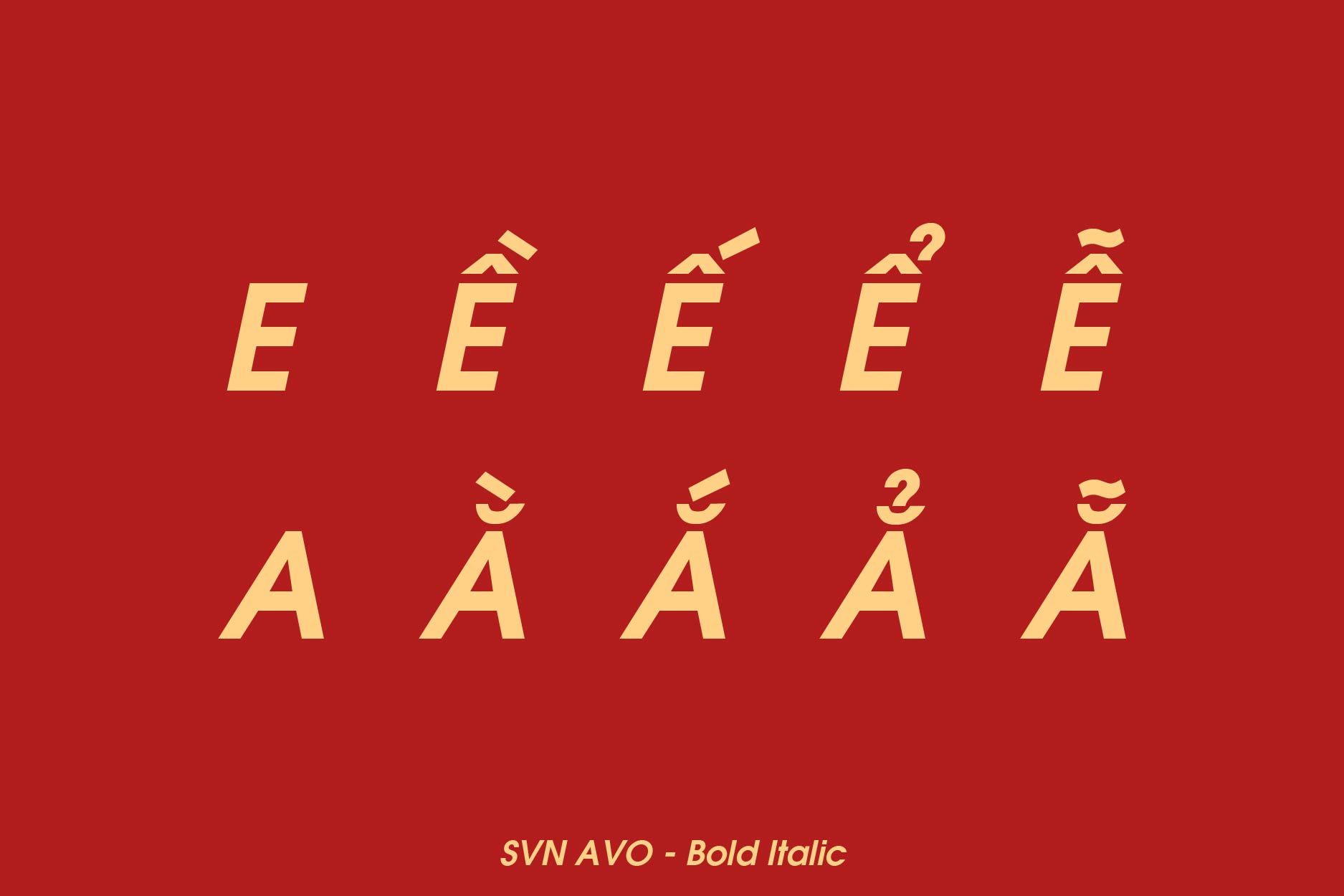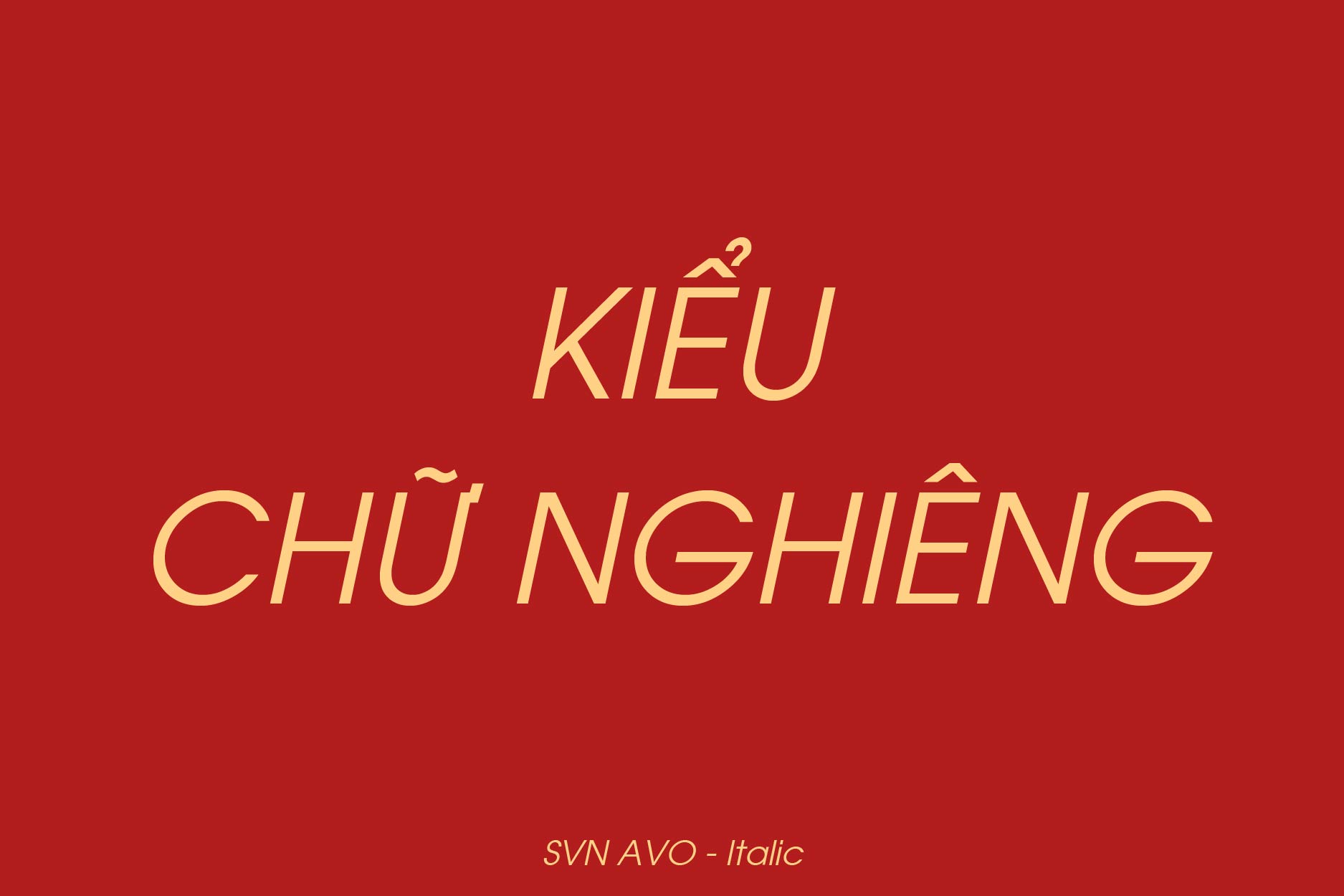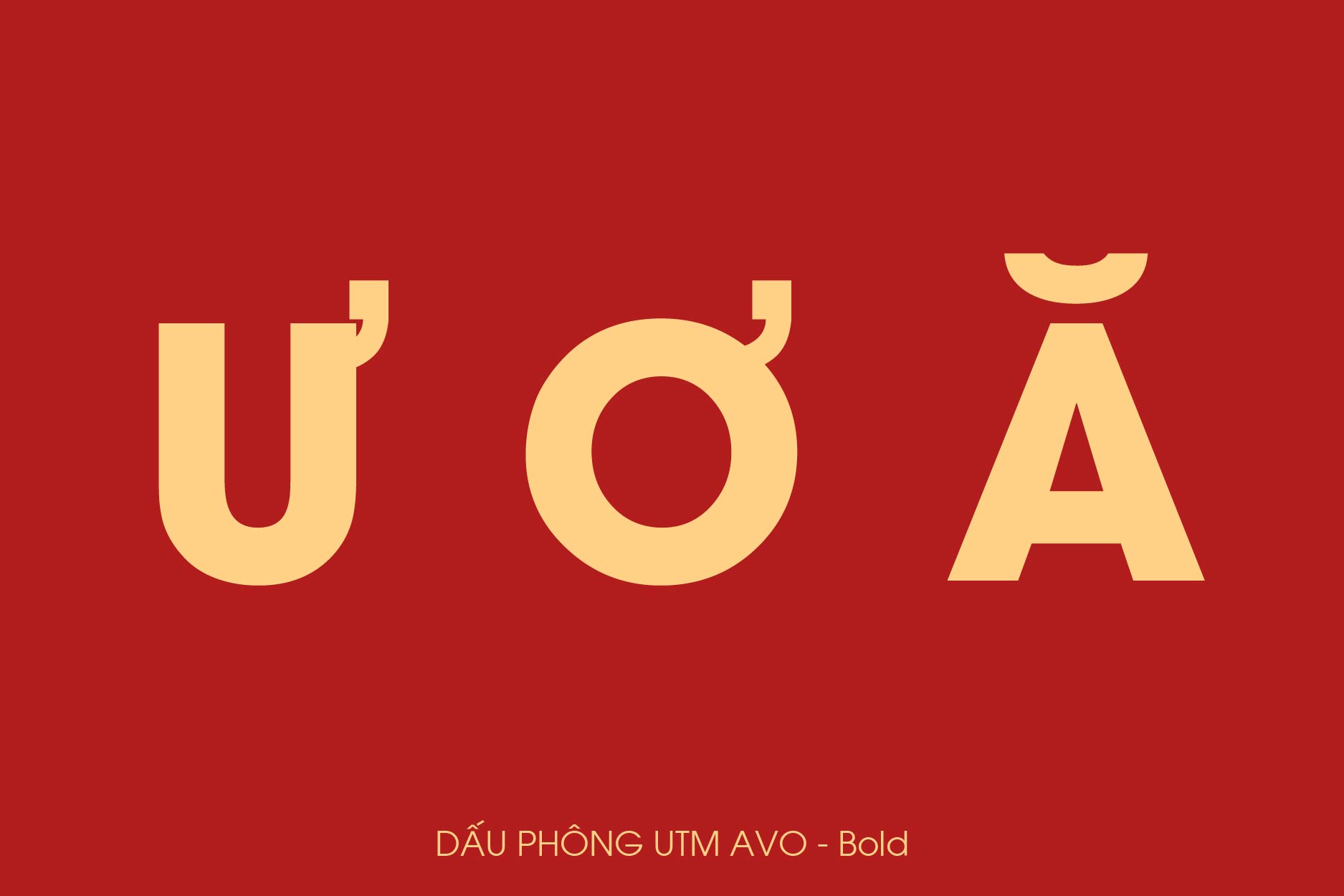
Trong thiết kế đồ họa và trình bày bản vẽ kiến trúc, sự rõ ràng và tối giản luôn là yếu tố được ưu tiên để đảm bảo tính chính xác của thông tin. Font SVN Avo Việt hóa là một bộ font chữ Sans-serif mang đậm phong cách hình học hiện đại, giúp văn bản trở nên thông thoáng và chuyên nghiệp.
SVN Avo
Đặc tính thẩm mỹ của dòng font SVN Avo Việt hóa
Sức hút của dòng font này đến từ cấu trúc hình học căn bản với các đường nét tinh gọn, mang lại cảm giác vững chãi và hiện đại. Khác với các kiểu chữ trang trí cầu kỳ, svn avo font tập trung vào khả năng thu hút thị giác trực diện, giúp các thông tin chính hiển thị tách bạch và dễ tiếp nhận. Phiên bản Việt hóa bởi đội ngũ SVN đã xử lý tinh tế hệ thống dấu thanh tiếng Việt, giúp các ký tự có dấu luôn giữ được sự cân đối và đồng nhất về mặt hình học so với bản gốc.
Sự ổn định của SVN Avo còn thể hiện qua khả năng hiển thị rõ nét trên cả môi trường in ấn lẫn các thiết bị kỹ thuật số. Dù được sử dụng ở kích thước lớn cho tiêu đề hay kích thước nhỏ cho các dòng ghi chú kỹ thuật, bộ font này vẫn duy trì được độ sắc sảo, hạn chế tối đa hiện tượng nhòe nét. Đây là lựa chọn phù hợp cho những dự án đề cao tính công năng, phong cách tối giản và tư duy kiến trúc hiện đại.
| Phân loại phong cách | Geometric Sans-serif / Minimalist |
| Kiểu chữ chính | Avo Regular, Bold, Italic, Bold Italic |
| Mục đích phù hợp | Bản vẽ CAD, Hồ sơ năng lực, Tiêu đề tối giản |
Gợi ý thiết kế: Nhờ tính chất trung tính và hiện đại, bạn có thể kết hợp svn avo bold italic việt hóa làm điểm nhấn cho các từ khóa hoặc thuật ngữ đặc thù, trong khi các kiểu Regular sẽ dùng cho phần nội dung thuyết minh chi tiết để tạo sự phân cấp mạch lạc.
Nhờ vẻ ngoài khoa học và sự rõ ràng trong cấu trúc nét, bộ font này mang lại giá trị thực tế cao khi được đưa vào các khâu vận hành và trang trí công trình hiện đại:
- Ghi chú thông số trên bản vẽ kỹ thuật: Sử dụng font svn avo bold ttf cho các chỉ dẫn về kích thước vật liệu panel, thông số kết cấu thép giúp bản vẽ trở nên rõ ràng, hỗ trợ đắc lực cho đội ngũ thi công tại hiện trường.
- Thiết kế hồ sơ năng lực: Dùng font chữ này cho các tiêu đề chính giúp nội dung trình bày có sự phân cấp rõ ràng, thể hiện phong cách làm việc ngăn nắp và tư duy kiến trúc chuyên nghiệp của đơn vị.
- Hệ thống biển hiệu văn phòng và Homestay: Các nét chữ hình học của SVN Avo rất ăn ý khi được cắt chữ nổi hoặc làm biển chỉ dẫn cho các công trình nhà lắp ghép nghỉ dưỡng mang phong cách hiện đại.
- Tối ưu hóa độ tương phản: Bạn có thể tạo điểm nhấn bằng cách phối hợp giữa độ đậm của svn avo bold 1 cho tiêu đề chính và kiểu chữ mảnh hơn cho các phần thông tin phụ để tạo ra bố cục phân cấp rõ ràng.
- Chú trọng khoảng trắng: Vì là dòng font mang tính hình học tối giản, bạn nên để khoảng trắng xung quanh các tiêu đề rộng rãi, tránh việc trình bày quá dày đặc sẽ làm giảm tính thanh lịch của bộ chữ.
- Kiểm soát khoảng cách dòng: Thiết lập khoảng cách dòng thoáng một chút để các dấu tiếng Việt không bị chồng lấn, giúp tổng thể bản vẽ trông thông thoáng và dễ đọc hơn khi nhìn từ xa.